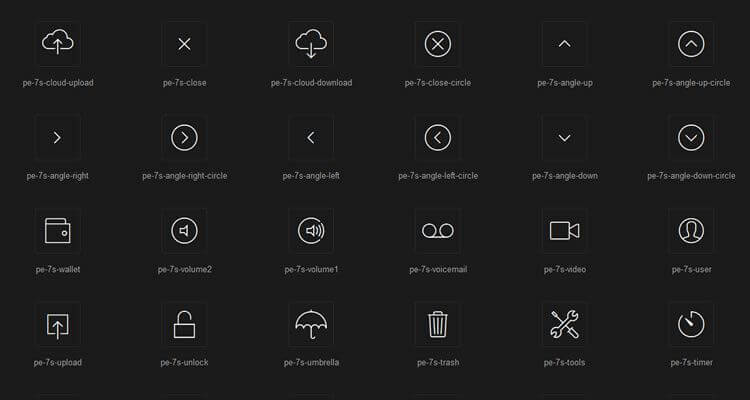
【デザインに差をつける】WEBデザインのための無料で使えるアイコンフォントTOP 56選
アイコンフォントはとても人気がありますが、同時に危険な落とし穴も含んでいます。イアン・フィーザーは自身がアイコンフォントからSVGに移行した理由を語っていますし、CSS TricksはアイコンフォントかSVGのどちらかを選ぶ時の基準の考え方を提示しています。イアンもCSS Tricksも、明らかにSVG派なのです。一方、Pictonicは「アイコンフォントはSVGより10%速い」と反論しています。いずれにせよこれらの事情は、あなたがアイコンフォントを使用したいのであれば、前もって知っておく必要があります。
LineAwesome (600 個)
Dashicons – WordPress 公式の認定アイコンフォント (197 個)
Linea Iconset (730+ 個)
Themify Icons (320+ 個)
GitHub’s Octicons (178 個)
Devicon (105 個)
iOS7 Vector Icons (100 個)
Genericons (120 個)
Stroke 7 Icon Font (170 個)
Stroke Icons (80 個)
Icon-Works (134 個)
Devicons – WEB開発者にとっての象徴的フォント (123 個)
Solid Icons (210 個)
77 Essential Icons (77 個)
Tonicons Outline Icons (200 個)
Stroke 7 – iOS7風の細線Strokeアイコンフォント(170 個)
The Elegant Icon Font (360 個)
Dripicons – 完全無料のVector線画アイコンフォント(95 個)
Iconia – レギュラー、円形、カットの3つのスタイルがあるアイコンフォント(113 個)
Metrize Icons – メトロスタイルなアイコンフォント (300 個)
Icon Pack – Petras Nargelaによる線画アイコンフォント (40 個)
Ionicons – Ionフレームワークのための大きめアイコンフォント (528 個)
Batch Icons (300+ 個)
IcoMoon Free Pack (450個)
MFG Labs Web Icon Set (120 個)
Font Awesome Free Icon Font (500+ 個)
Foundation Icons (140 個)
Ligature Symbols (250+ 個)
OpenWeb Free Icon Font (54 個)
Sosa Free Icon Font (120 個)
One Div (91 個)
PW Drawn Icon Font (80+個)
Premium Pixels Mini Icons (80個)
Fontelico Font (30個)
Typicons (88個)
Icons V.3 –Hüseyin Yilmazによる無料アイコンフォント (24 個)
Genericons – WordPressによるアイコンフォント (123 個)